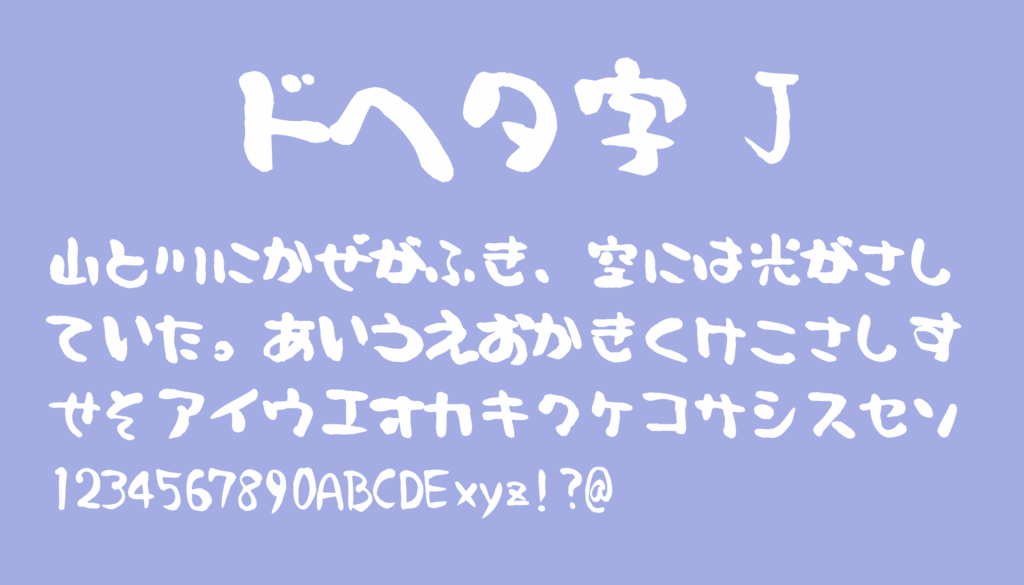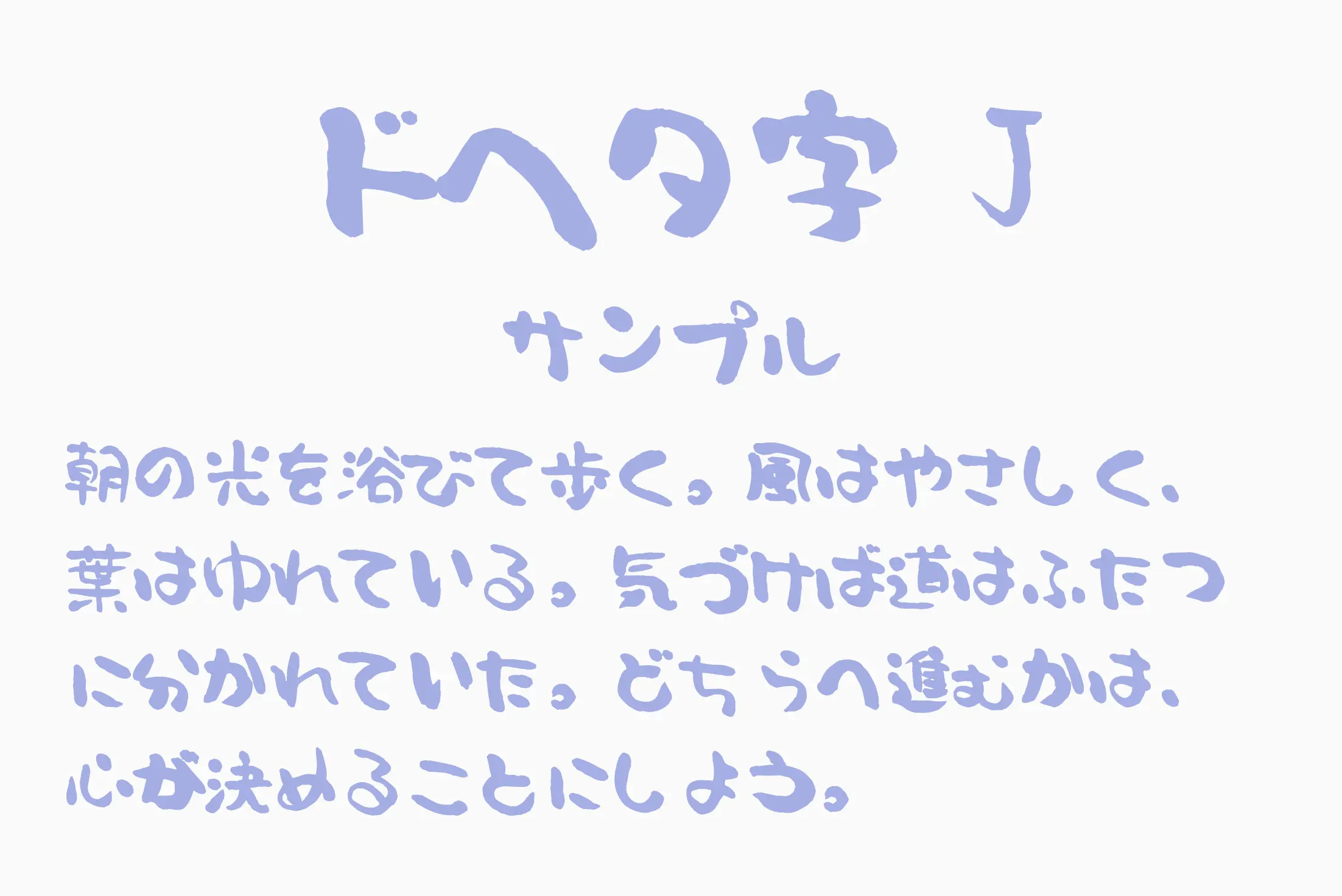
名前の通り“ド下手”な味わいを持つ手書き風フォントです。雑な線、バランスの崩れた文字が逆に個性となり、コミカルさやユーモア、ゆるさを演出したい場面にぴったり。特に子供向けコンテンツやポップなデザイン、脱力系イラストなどと相性がよく、意図的に“下手さ”を使いたいときに重宝します。癖が強いながらも、読みやすさも確保されており、タイトルや見出しにも活用できます。
ドヘタ字 J